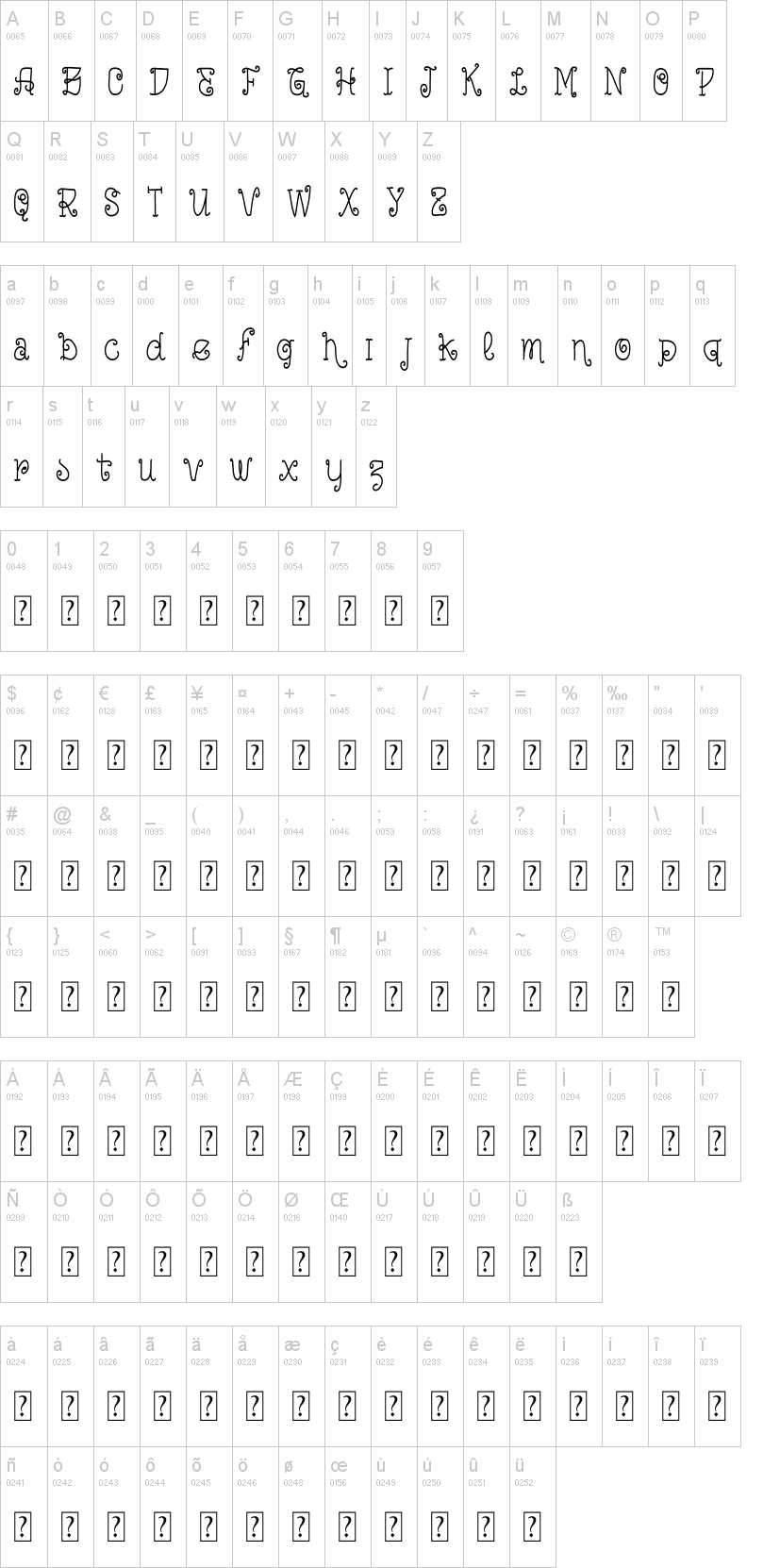
Vtks Love is EveryThing
Vtks Love is EveryThing 是一款免费的手写风格字体,由巴西设计师Douglas Vitkauskas创作。该字体的特点是由手写草书风格的字母组成,整体风格比较自由、温馨和浪漫。这款字体适合用于设计浪漫、情感、个性化和手工制作感觉的设计项目,如情书、婚礼邀请函、手写笔记等。Vtks Love is EveryThing 字体支持多种语言,包括英文、葡萄牙语、西班牙语、德语、法语等。
Vtks Love is EveryThing是一款非常不错的手写艺术字体,具有很好的视觉感,适合于文化类的宣传设计、商业类品牌的广告和产品包装设计以及个性化文字排版等较多场景。